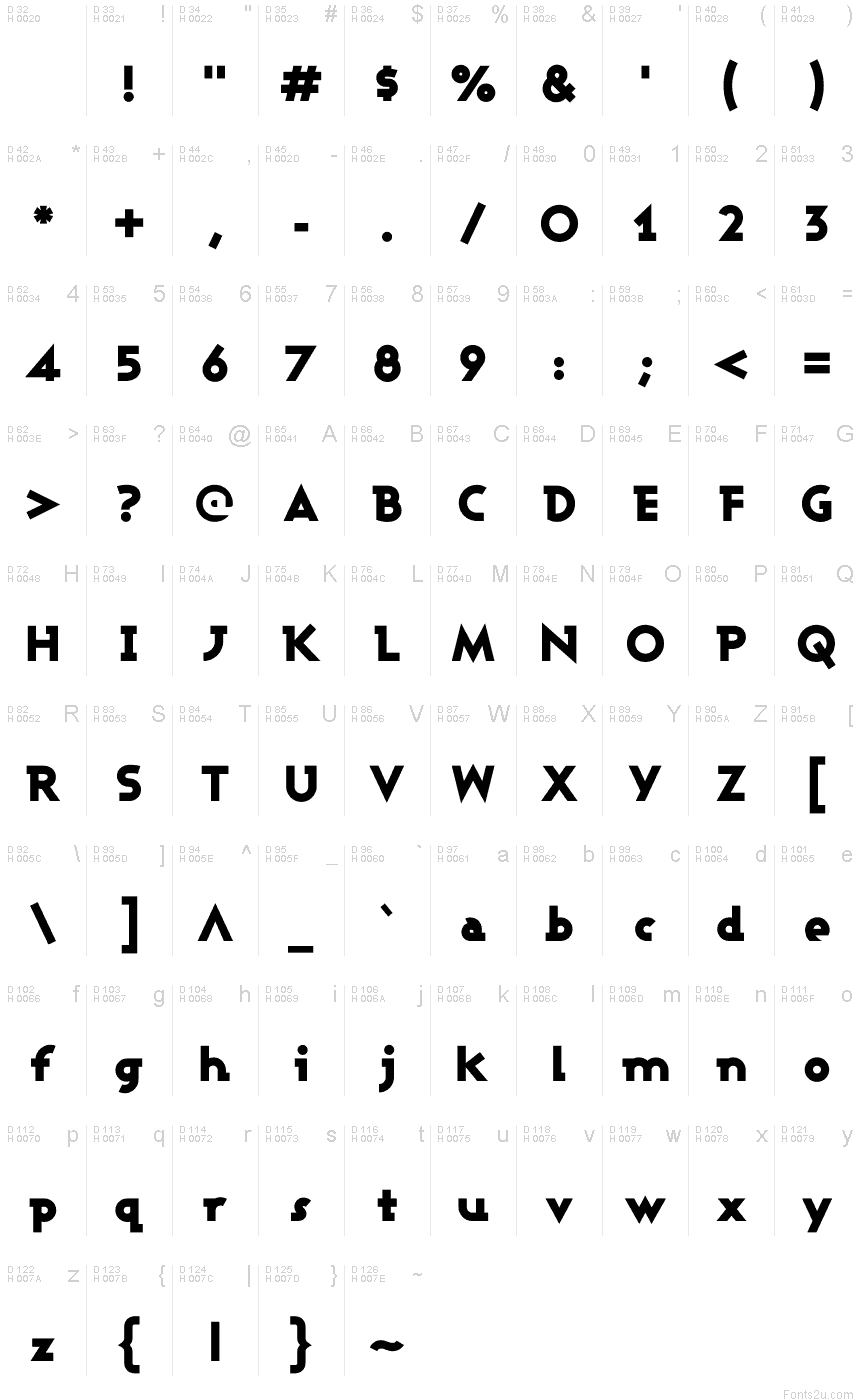
Ashby Black
Ashby Black od Robby’ego Woodarda z Apostrophic Laboratories to darmowy, retro krój displayowy, który przyciąga wzrok swoją masywną, wyrazistą formą i pewnym siebie, geometrycznym stylem. Zdecydowane krzywizny, ciasny rytm i trójkątne wycięcia nadają każdej literze uderzający, niemal szablonowy charakter, a rodowód rodziny Ashby zapewnia spójność i czytelność już na pierwszy rzut oka. Odważne kształty i szerokie światła wewnętrzne tworzą silną sylwetkę, która mimo wszystko pozostaje zabawna – jakby vintage’owe szyldy zostały zaprojektowane na nowo dla nowoczesnych ekranów.
Dzięki Ashby Black nagłówki natychmiast wskakują na swoje miejsce i przykuwają uwagę bez konieczności stosowania dodatkowych efektów. Ten darmowy krój doskonale sprawdza się na plakatach, okładkach płyt, w brandingu, na opakowaniach, w dużych tekstach typu hero na stronach www oraz w wyrazistych grafikach do mediów społecznościowych. Pozwól Ashby Black przejąć „głośne”, duże formaty, a w tekstach głównych zestaw ją z czystym, lekkim bezszeryfowym krojem, aby zachować równowagę i zapewnić przyjemność czytania.